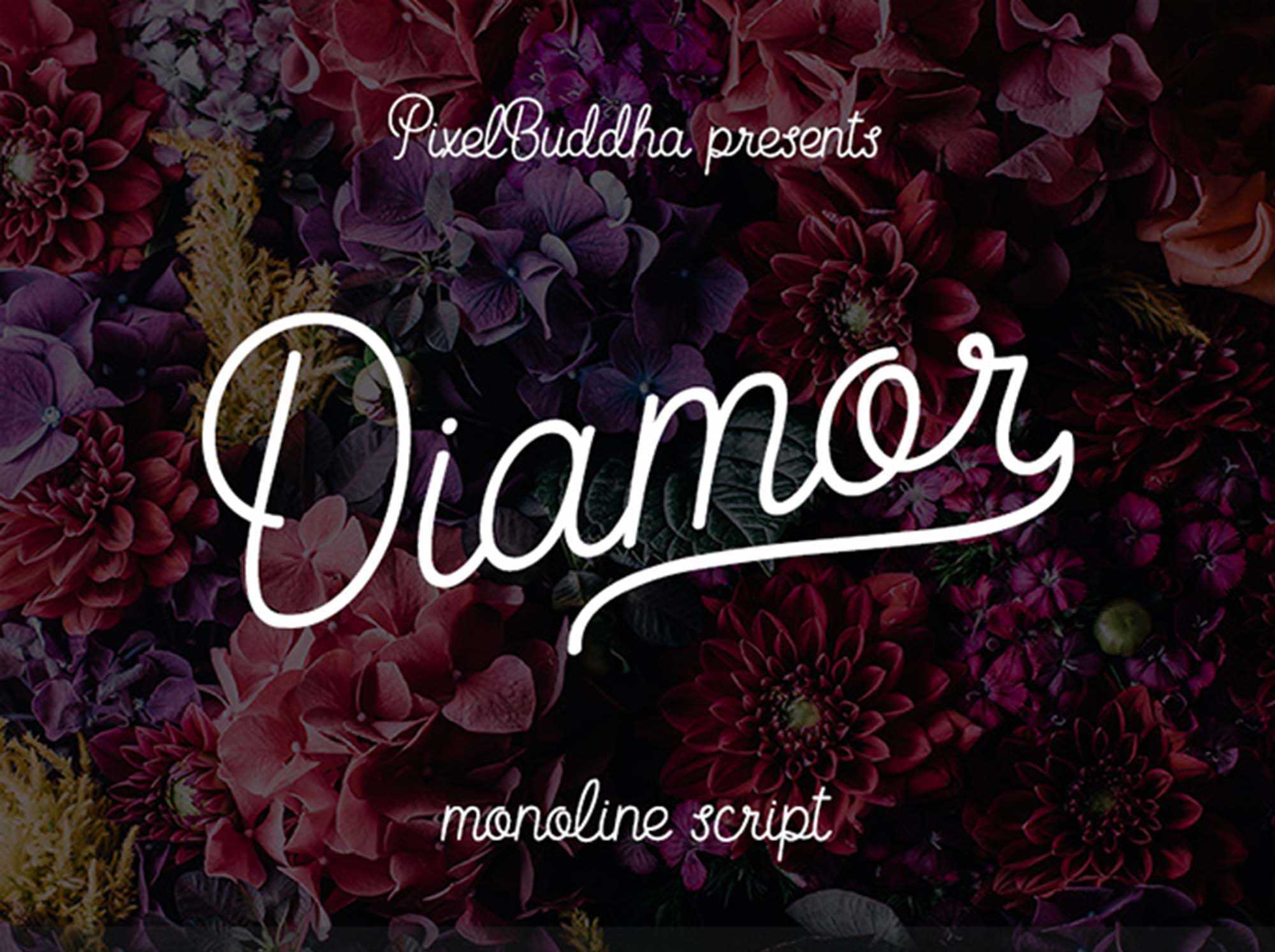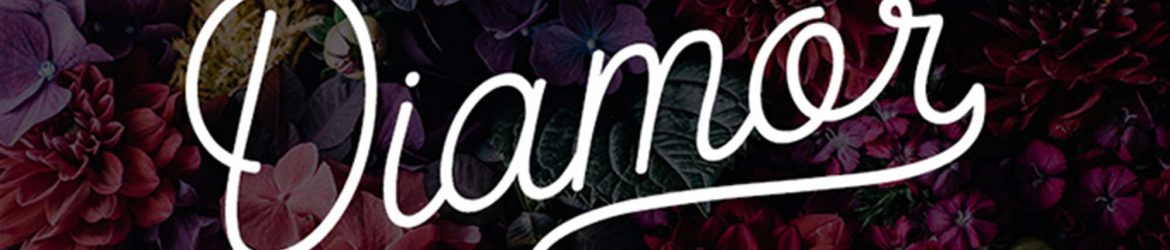
Diamor Free Script Font é uma fonte elegante que permite você explorar o mais romântico e intenso dos idiomas: o francês. Com sua música interna nos sons das palavras, ela se destaca como uma fonte que toca os corações dos que a utilizam. Seja para um design de capa de livro ou até mesmo para criar um selo de biscoito, essa fonte oferece um toque especial e único. Ela ilustra a ideia de que o amor é para cada lugar e para cada pessoa, e que o francês é a linguagem romântica mais poderosa. Como um artigo de arte em si, ela é perfeita para ser mostrada no seu trabalho. Diamor Free Script Font é uma fonte que traz beleza à sua obra, e ela está aqui para transformá-la em algo mais especial.